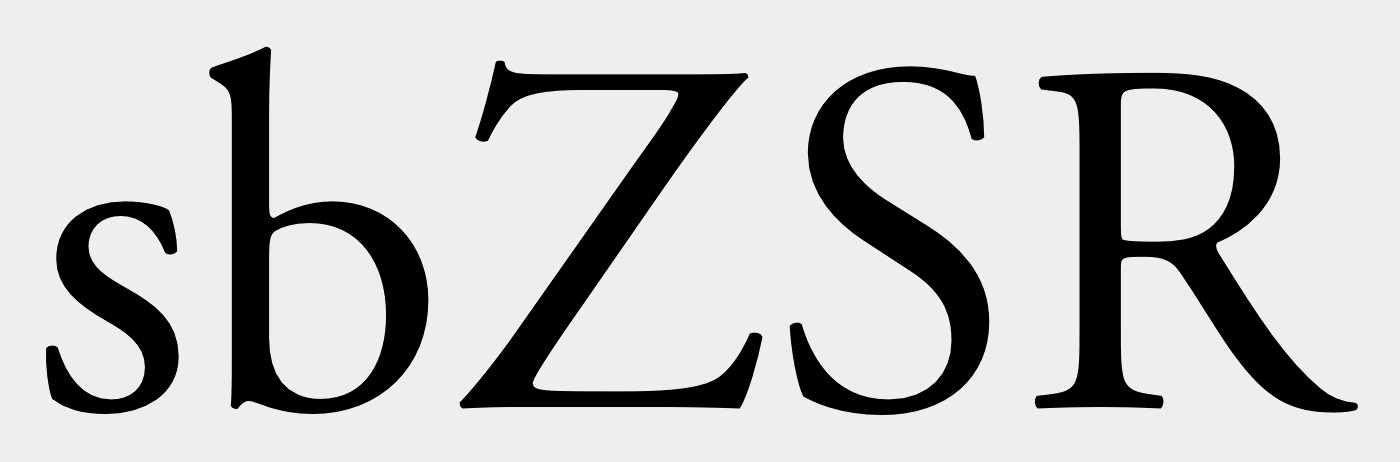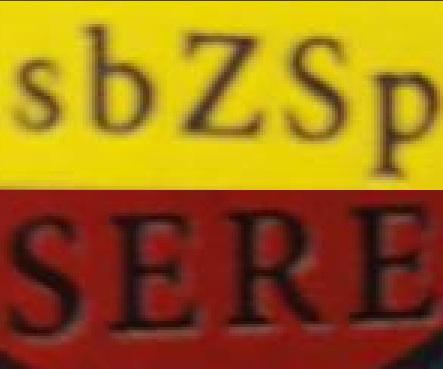
Was sind das für zwei Schriftarten?
ich heiße Vanessa bin neue hier und kenne mich noch nicht so gut aus. Ich suche zwei solche Schriftarten wie auf dem Schild.
Das R im unteren Beispiel sieht eher aus wie eine Times … was dann wohl mit den Serifen am S passiert ist?